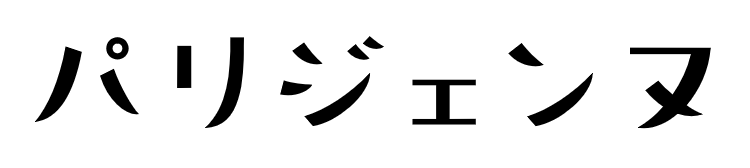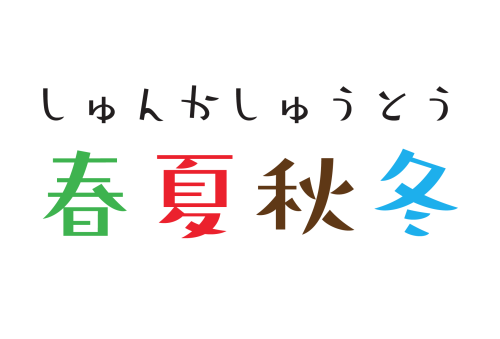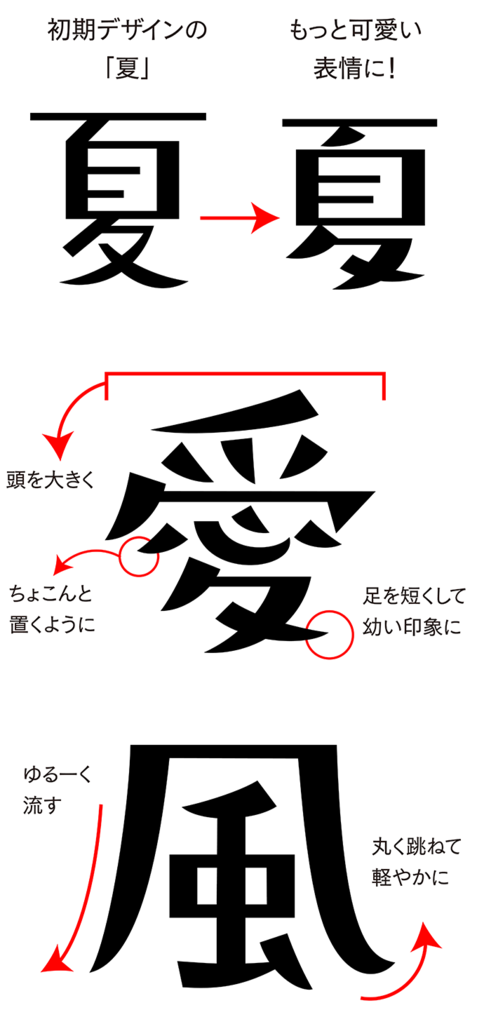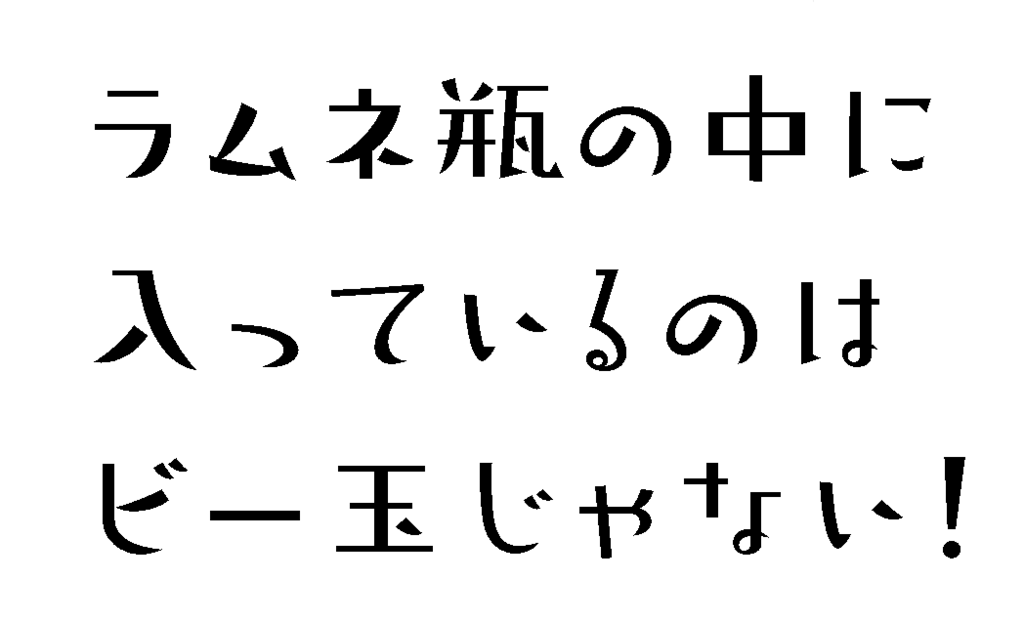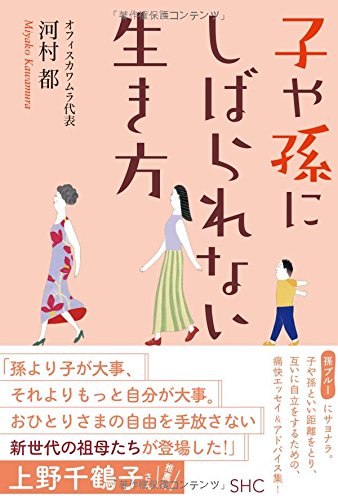
パルラムネ
フォントワークスWebサイト内にあるフォントコラムにて、フォントワークス所属の書体デザイナー越智亜紀子氏の新作フォント「パルラムネ」が紹介されている。
2016年6月13日(月)に放送されたNHKの「プロフェッショナル 仕事の流儀」で放送された「異端の文字、街にあふれる 書体デザイナー・藤田重信」の回でも、藤田氏と越智氏のやりとりとともに開発中のパルラムネも公開されていたが、いよいよパルラムネが完成したようだ。
パルラムネの特徴
フォントワークス入社6年目の越智氏が初めてリリースするフォントで、「今風の脱力感!」をコンセプトに「ゆるい雰囲気」と「あどけない愛らしさ」が魅力の脱力系のデザインフォントになっている。
漢字と仮名で異なるサイズの凸凹感が文字を組んだ際にリズミカルな表現になり、なんとも言えない抜け感が見た人の心を掴む、軽やかに跳ねたテンとハライの特徴がタイトルやキャッチコピーを適しており、使いやすそうなフォントだ。
コラムでは、筑紫書体デザイナーでありフォントワークスの書体デザイナー藤田重信氏との会話で得たヒントを含む制作秘話、書体デザイナーになったきっかけなどを紹介している。
▼コラムで公開された制作コンセプト
ラムネの名前の由来
そんなパルラムネをぜひ、ご当地ラムネなど様々なラムネのタイトルにも使用してほしい。
パルラムネ使用事例「子や孫にしばられない生き方」
川村都氏著書、産業編集センター出版による2017年7月13日発売の「子や孫にしばられない生き方」のタイトルフォントとしてパルラムネが使用されている。